¿Quieres personalizar la funda o la carcasa de tu teléfono celular con una frase única e impactante? Puedes hacerlo tú mismo/a si te gusta el hand lettering y tienes los materiales necesarios a mano. Sigue este vídeo y estos consejos que te doy para personalizar la carcasa a tu gusto. ¡Vamos allá!
Consigue una carcasa de plástico y límpiala bien
Antes de empezar con el hand lettering, es importante que limpies bien la carcasa con alcohol para retirar cualquier resto de suciedad que viene de fábrica o la propia grasa de las manos. Se secará rápido.
Elige un rotulador acrílico
Lo siguiente para realizar un hand lettering personalizado en la carcasa de tu teléfono es hacerte con unos buenos rotuladores acrílicos. Aunque los Posca de Uniball son los más conocidos y son los que utilizo yo en el tutorial, si no los puedes conseguir, hay otras muchas marcas que tienen rotuladores acrílicos, como Sharpie con sus Marcadores creativos acrílicos, BIC con sus Intensity Paint, entre muchos otros. Lo importante es que la punta no sea demasiado gruesa, así que si usas los POSCA, busca los que tengan punta de 0,7 mm o los de 0.9-1,3 mm, ambos bullet shaped.
Haz un borrador en un folio
Marca el contorno de la carcasa en un papel para poder hacer el borrador del diseño que deseas realizar. Esto te va a ahorrar mucho trabajo, créeme. Con un lápiz, escribe la frase que has elegido. En este caso, yo escogí la de «Baby no me llames» de Rosalía, pues me hacía gracia poner eso en la carcasa de un teléfono. Combiné letra script (manuscrita) en minúsculas con un efecto un poco bouncy con una palabra en mayúsculas para enfatizar la palabra «NO».
Llega el momento de hacer el hand lettering definitivo
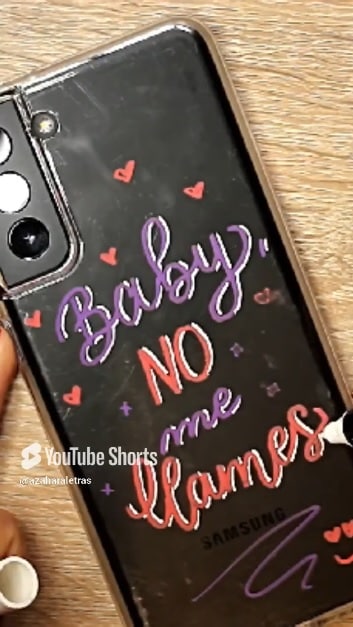
Una vez tienes el borrador de papel, si la carcasa es transparente, puedes ponerlo debajo e ir calcando el diseño. Lo importante en este paso es que la tinta del rotulador acrílico fluya bien para escribir las palabras con soltura. Si te equivocas, no te preocupes, ya que con un bastoncillo de algodón empapado en alcohol puedes limpiarlo rápidamente y corregir.
Fíjate bien en que, una vez acabada la frase del borrador, procedo a realizar sombras a derecha de color blanco para que el hand lettering quede mucho más expresivo y elaborado.
También es importante destacar que si la frase queda un poco sosa o que quedan mucho espacio en blanco, se puede rellenar con pequeños dibujos como estrellas o corazones para que la carcasa quede completa.
Barnízalo con spray de acrílico
Para que el lettering que acabas de realizar no se borre con el uso y con el roce, es necesario que lo barnices. Para ello, lo mejor es usar un barniz en spray transparente especial para acrílicos. Verás que los hay en acabado brillo o en mate, elige el que más te guste y sigue las instrucciones del fabricante, pues varían según el material y en tiempo de secado.